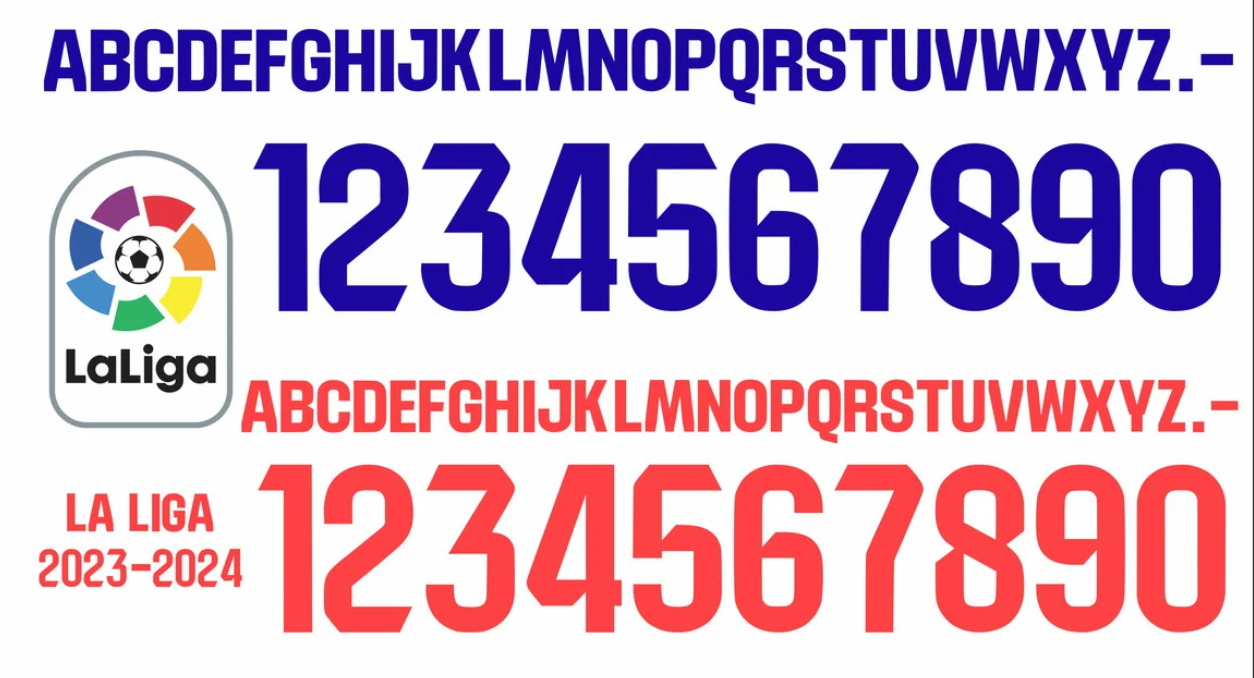
A temporada 2023-2024 marcou o início de uma nova era para o futebol espanhol. A LaLiga passou por um rebranding completo, abandonando o antigo círculo colorido para adotar o novo símbolo “LL” e uma identidade visual muito mais moderna, digital e agressiva.
Acompanhando essa mudança radical, a tipografia oficial da liga também foi renovada. Esta é a fonte padronizada utilizada nas costas das camisas da grande maioria dos clubes durante as partidas do campeonato, vestindo times tradicionais como Atlético de Madrid, Sevilla, Real Betis, Real Sociedad e Valencia.
Estilo Visual e Aplicação
A nova fonte da LaLiga rompe com as curvas suaves das temporadas anteriores. Ela apresenta um design sólido, condensado e com cortes angulares que transmitem velocidade e força. É uma tipografia desenhada para ser legível tanto em telas de smartphones (foco da nova marca) quanto nas arquibancadas dos estádios.
Ela é ideal para ser aplicada em camisas de futebol (kits Home, Away e Third), mas também funciona muito bem em banners de escalação (“Match Day”) e artes para redes sociais, pois possui uma presença visual marcante sem ser excessivamente decorativa.
Dica de Especialista: Para uniformes de times que jogam competições europeias (como a Champions League), verifique se o clube utiliza esta fonte da liga ou uma fonte própria da fornecedora (como Adidas, Nike ou Puma), já que em torneios continentais a padronização da liga não é obrigatória.